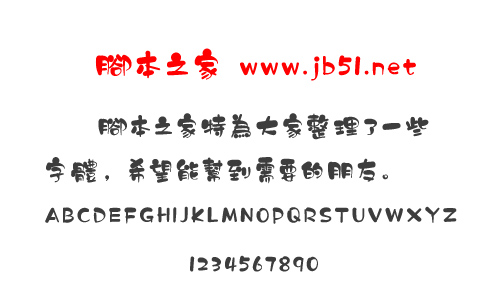
銳字溫帥可愛繁字體是一款非常受歡迎的中文字體,適應(yīng)于很多節(jié)目、項(xiàng)目、設(shè)計(jì)使用,銳字溫帥可愛字體字形溫潤(rùn)飽滿、親切乖巧,筆畫不拘一格、粗細(xì)對(duì)比協(xié)調(diào)、簡(jiǎn)化變形有新意且不失識(shí)別性,營(yíng)造了一種輕松歡快、充滿趣味性的氛圍,較之銳字溫帥小可愛字體繁缺少了高光和立體感,不過也是不錯(cuò)的,可以廣泛應(yīng)用于制版印刷、產(chǎn)品包裝、平面設(shè)計(jì)、藝術(shù)設(shè)計(jì)等領(lǐng)域,歡迎大家前來下載使用。